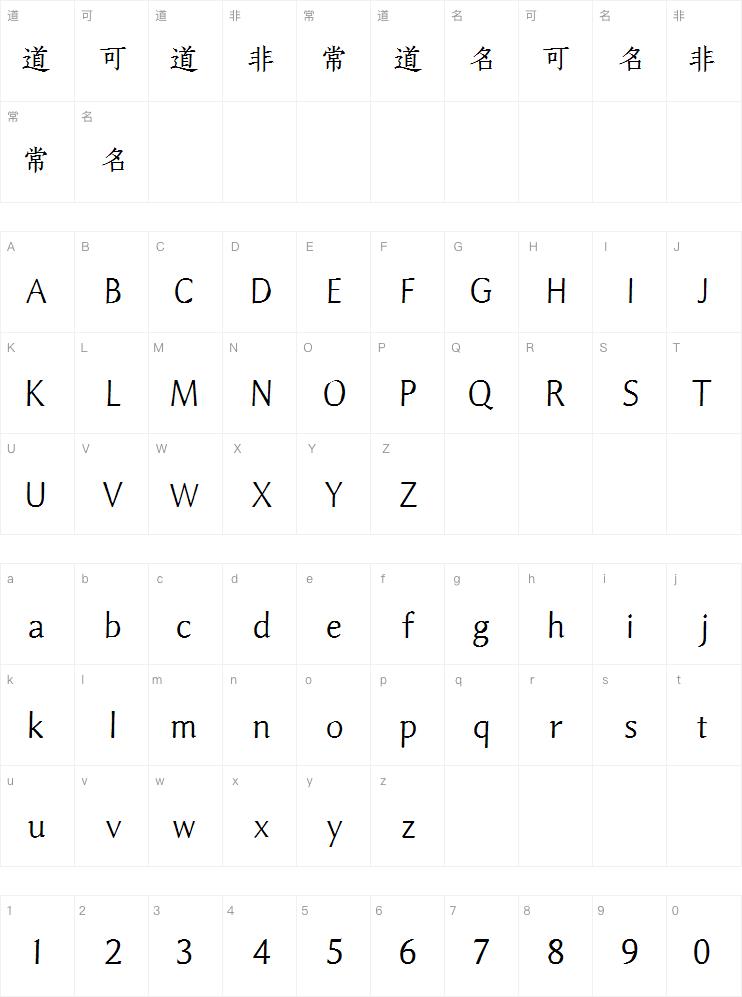
山海汲古宋刻 简繁
山海汲古宋刻 简繁,是一款全新的字体,包含简繁汉字9414个,符号200+个,是一款国风复古刻本字体。是由上海拾岁科技有限公司独立设计和制作。字形秉承中国宋代古籍善本之字形特性,版刻刀法剔透,字形方正,端庄严谨,古朴大方,起落顿笔有棱角。在饱有笔墨之意的同时,又突显刀刻之锋美,笔刀结合刚柔并济。在秉承笔形间创新,结合当代设计视觉环境,融入现代审美,适用场景更多元,笔画造型清晰锐利,删繁取简,笔锋凌厉,速度感强,粗细对比强烈,重现刀刻古韵之美。